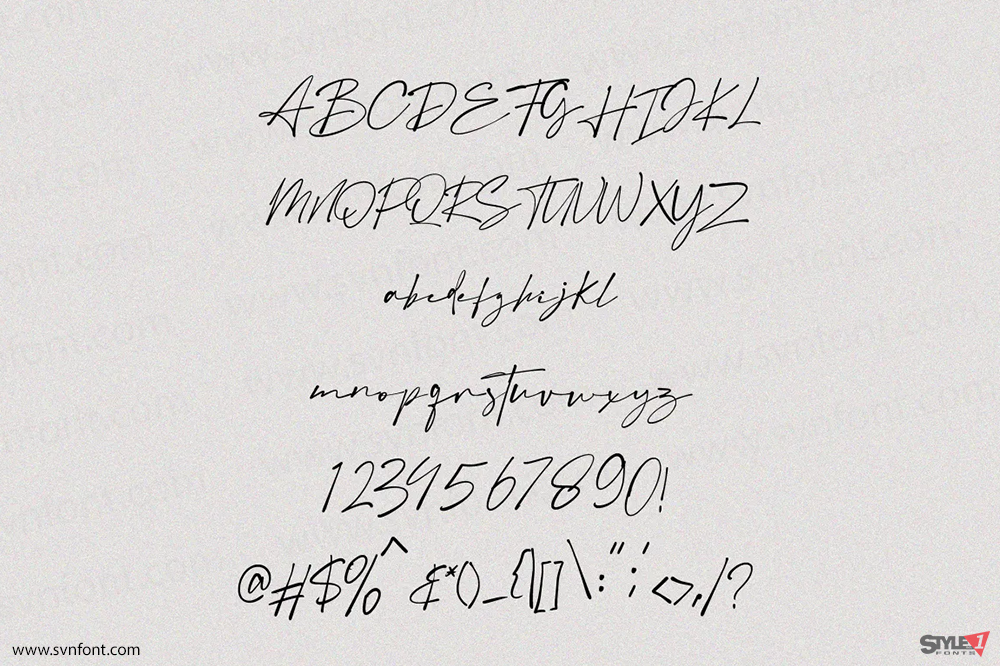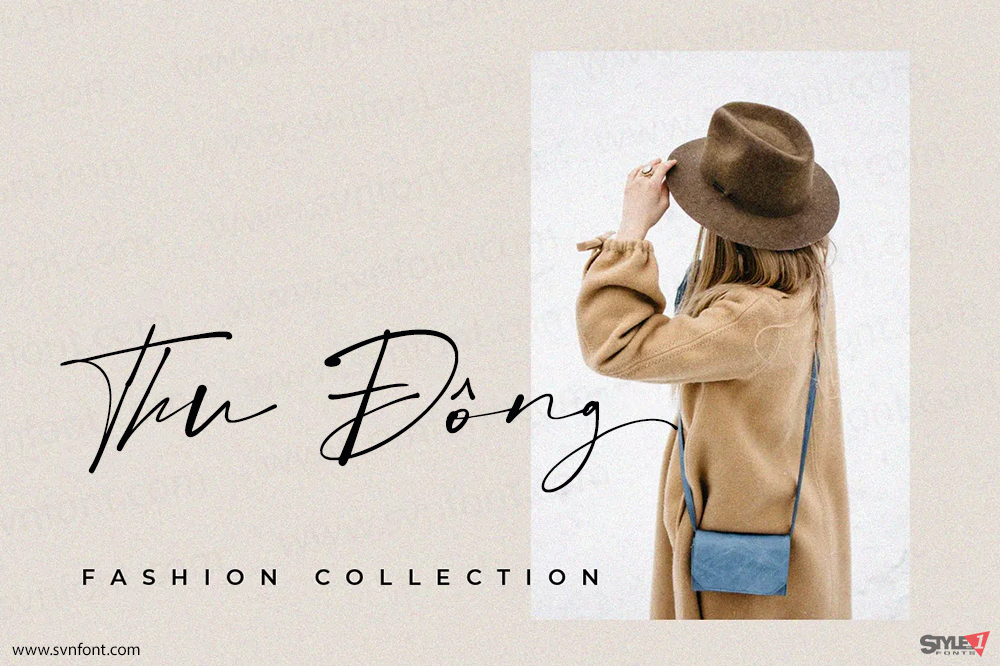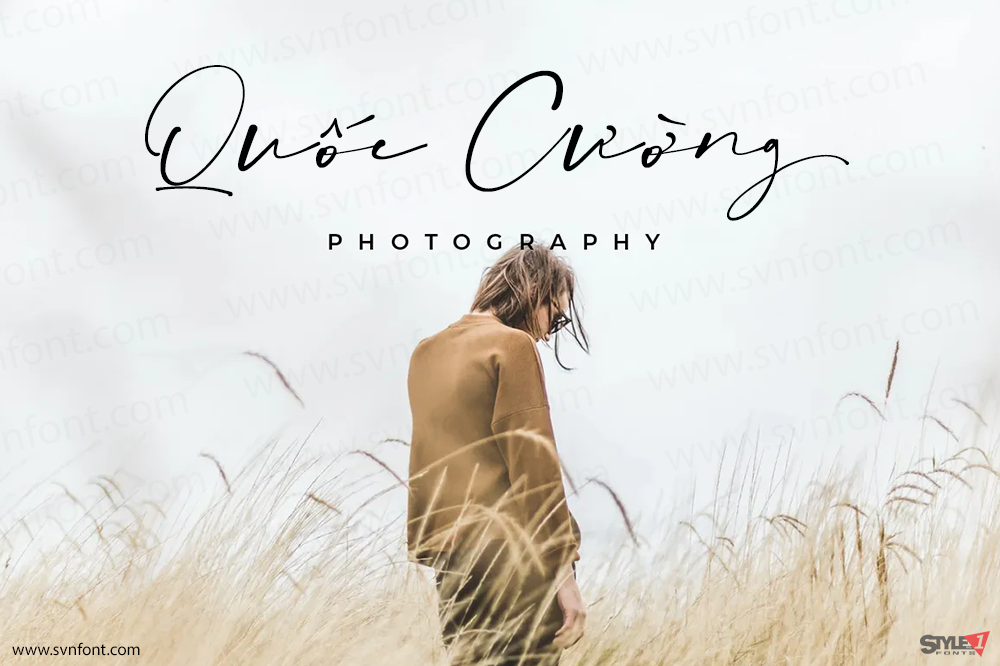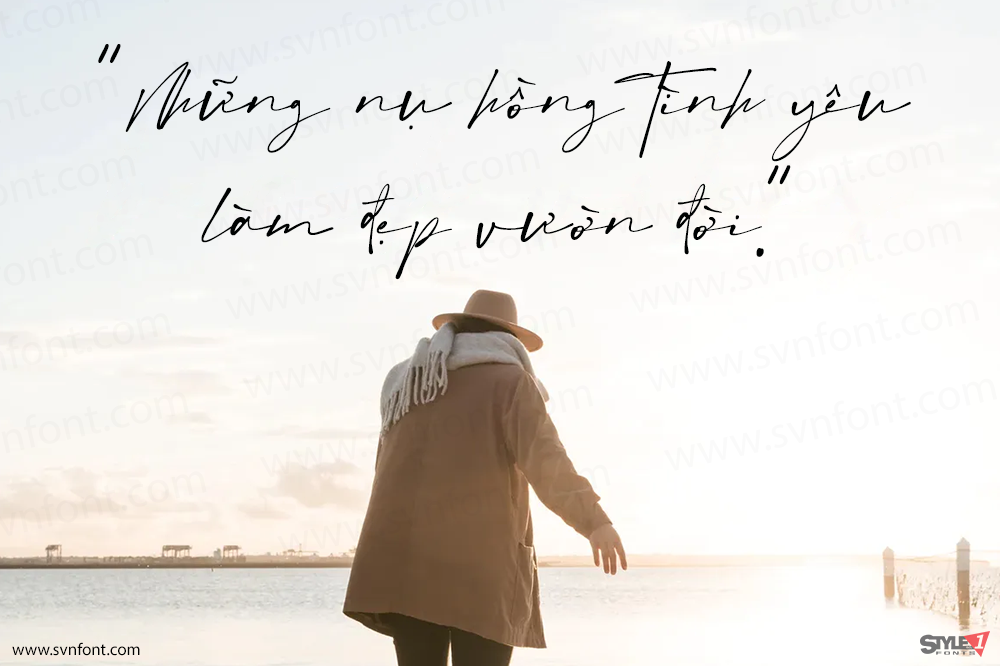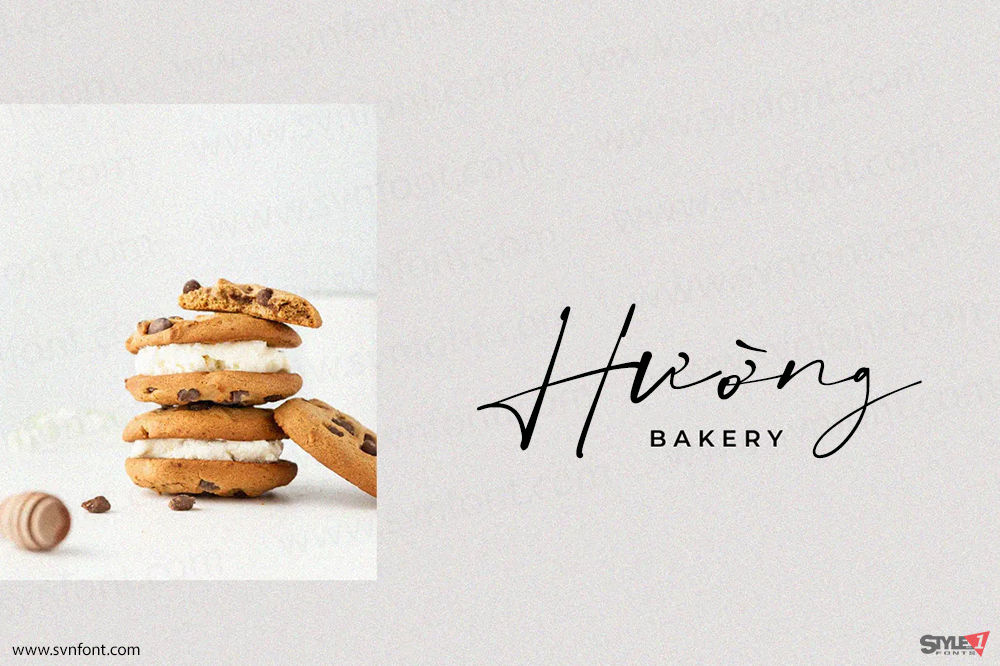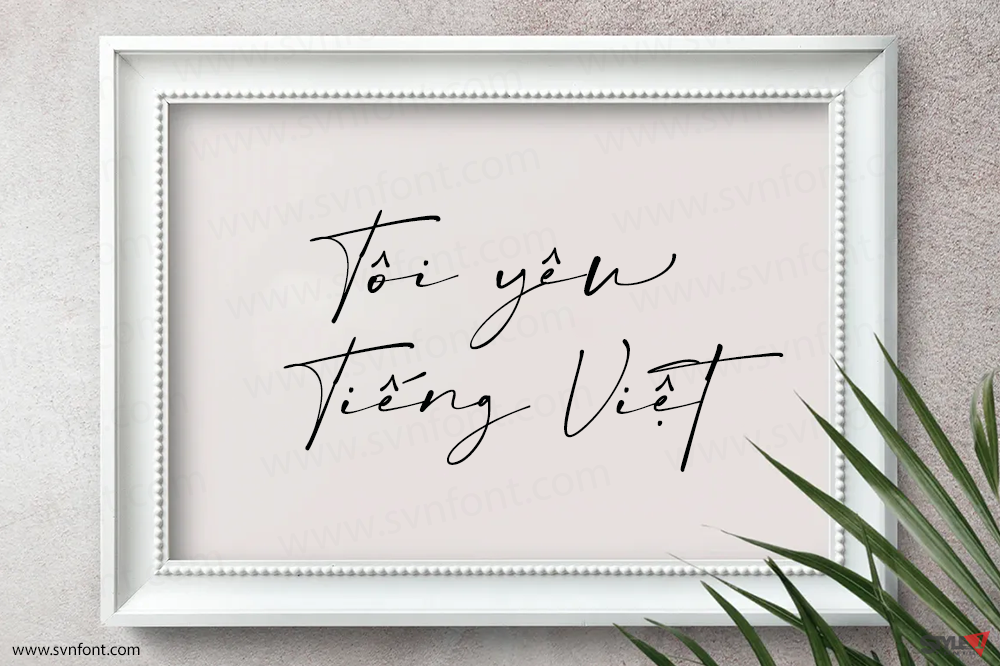
Austin Signature là một font script (kiểu chữ viết tay) tối giản với các nét nối (ligature) và font thay thế (alternate font) đẹp mắt. Các font chữ viết tay đương đại với các nét nối và kiểu thay thế sẵn sàng thêm vẻ độc đáo và sự nở rộ vào thiết kế của bạn.
Font này dễ dàng kết hợp với nhau cho các Tiêu đề Tạp chí, Phim ảnh hoặc Sách. Dùng cho Nhiếp ảnh, Thiệp mời cưới, Thực đơn Nhà hàng hoặc Thiết kế Áo phông. Dùng cho Tờ rơi, Banner quảng cáo, web và in ấn. Từ Thực phẩm và Thời trang đến sản phẩm Mỹ phẩm.
Nhà thiết kế: Vultype Co
Nhà phát hành: Vultype Co